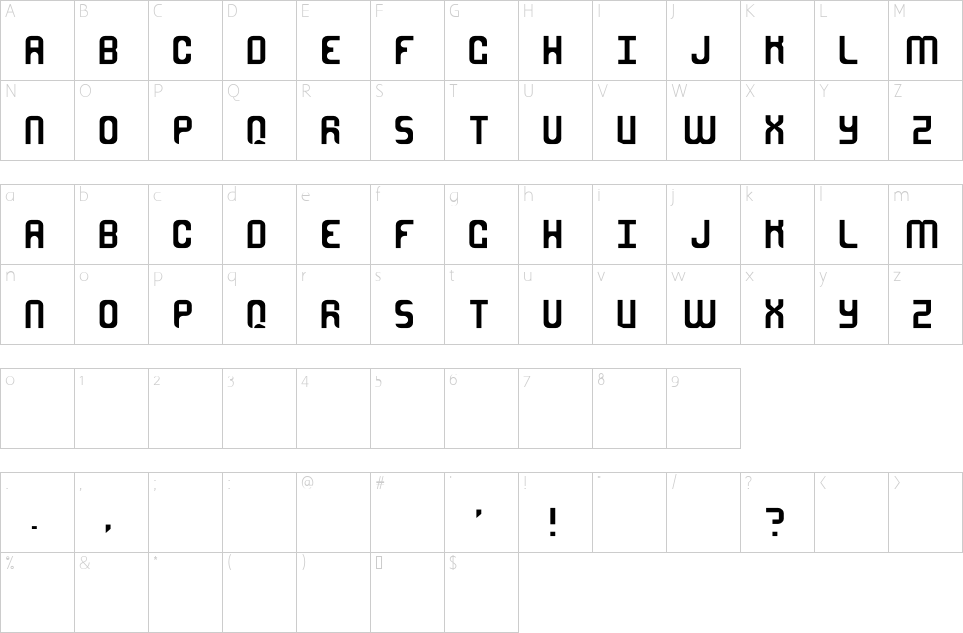
Metro Skies é uma fonte moderna e elegante que se destaca como uma excelente escolha para qualquer projeto de design gráfico. Desenvolvida por Skyhaven Fonts, esta font oferece linhas suaves e linhas elegantes que ajudam a destacar seu texto. Com um design minimalista, Metro Skies é ideal para criações digitais que exigem uma aparência minimalista e moderna. Se você está procurando por uma fonte clean e moderna para seus projetos de design gráfico, Metro Skies é uma fonte que você definitivamente não pode deixar de experimentar. Como fonte gratuita, é uma ótima opção para designers que buscam recursos para projetos pessoais ou comerciais. Com 1,819 downloads, provavelmente você encontrará ideias inspiradoras para utilizar esta font em seus projetos.